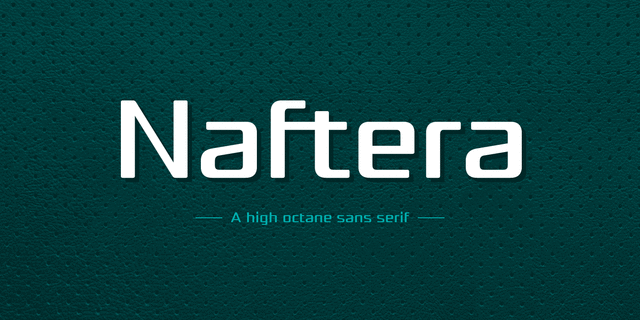
Это механический геометрический гротеск с росчерками и слегка закругленными углами, которые придают строгий, но изысканный вид. Naftera была задумана как шрифт для логотипов, заголовков и элементов экранного интерфейса, а также для коротких текстовых блоков. Семейство состоит из 10 начертаний. 8 начертаний содержат огромное количество глифов для разных языков, включая кириллицу, а также капитель и лигатуры. Другие 2 начертания бесплатные для использования на условиях десктоп-лицензии. Шрифт разработал Пабло Балселлс в 2019 году.
Ассоциации c начертанием Naftera LightКачества и характер:
ровный, точный, логичный, автоматический, техногенный, твердый, статичный, четкий, устойчивый, стабильный, тонкий, легкий, городской, современный, машинный, инженерный, урбанистический, чертежный, стеклянный, хрупкий, футуристичный, прозрачный, спокойный, проволочный, худой, гладкий, гибкий, чистый, модный, лаконичный, неоновый